Cele mai bune 36 de fonturi corporative 2023 (gratuit și premium)
Publicat: 2023-08-05Te-ai chinuit vreodată să găsești fontul perfect pentru proiectele tale corporative? Te-ai săturat de aceleași fonturi vechi care nu prea au impactul pe care ți-l dorești?
Ei bine, nu mai căutați! În această postare pe blog, am pregătit o listă cu cele mai bune 36 de fonturi corporative care vă vor duce proiectele de design la nivelul următor.
Indiferent dacă creați logo-uri, site-uri web sau materiale tipărite, aceste fonturi sunt garantate că vă vor ridica designul și vor face o impresie memorabilă.
În era digitală de astăzi, fonturile joacă un rol critic în succesul identității vizuale a mărcii. Ei pot comunica valorile, personalitatea și profesionalismul unei companii. Alegerea fontului potrivit poate face o diferență enormă în modul în care publicul vă percepe marca.
În această listă cuprinzătoare, am selectat cu atenție 36 de fonturi corporative care s-a dovedit că îmbunătățesc coerența mărcii, lizibilitatea și atractivitatea estetică generală. Aceste fonturi au fost folosite de companii de top din diverse industrii și au rezistat timpului.
Fie că sunteți în căutarea unui font îndrăzneț și modern care să transmită putere și inovație sau un font clasic și elegant pentru o senzație mai tradițională, veți găsi un font care se potrivește viziunii dvs. în acest articol.
Pregătește-te să descoperi fontul perfect care îți va ridica proiectele și va lăsa o impresie de durată asupra publicului tău. Lumea tipografiei este la îndemâna ta!
Cele mai bune fonturi premium corporative
Doriți să vă îmbunătățiți proiectele de design cu fontul perfect? Nu căutați mai departe decât lista noastră cu cele mai bune 36 de fonturi premium corporative. Aceste fonturi sunt îngrijite cu atenție pentru a adăuga o notă de profesionalism și sofisticare oricărui proiect.
Nu ratați oportunitatea de a vă îmbunătăți design-ul - verificați acum selecția incredibilă de fonturi din acest articol.
Parker
Parker este un font sans-serif uimitor care oferă amestecul perfect de eleganță și contrast. Proiectat special pentru scopuri de branding, este sigur că va adăuga o notă de sofisticare și modernitate oricărui proiect.
Cu gama sa largă de ligaturi și caractere alternative, acest font permite designerilor și proprietarilor de produse să-și dezlănțuie creativitatea și să creeze variații nelimitate care se aliniază perfect cu viziunea lor artistică.
Folosind Parker, te poți asigura că design-urile tale ies în evidență din mulțime și lasă o impresie de durată asupra publicului tău. Aspectul său îndrăzneț și distinctiv necesită atenție și creează un sentiment de încredere și fiabilitate.
Fie că este vorba despre un logo, un titlu sau un slogan, acest font va face, fără îndoială, o declarație și va spori atractivitatea vizuală generală a proiectului dumneavoastră.
Mod de gândire
Mindset este fontul perfect pentru designerii grafici care doresc să-și îmbunătățească proiectele cu un plus de profesionalism. Cu acest font, puteți crea fără efort logo-uri uimitoare care pot fi utilizate pe diverse platforme, cum ar fi site-uri web, printuri, reviste, postere și multe altele.
Proiectat special pentru logo-uri și branding, fiecare personaj este creat cu atenție pentru a asigura un design atrăgător și de impact vizual.
Când vine vorba de fonturi corporative sans serif, Mindset este un candidat de top. Liniile sale curate și structura îndrăzneață emană încredere și profesionalism, făcându-l ideal pentru companiile care doresc să facă o impresie puternică.
Indiferent dacă creați un logo pentru un startup tehnologic elegant sau o firmă de avocatură sofisticată, acest font cu siguranță vă va ridica designul și va capta esența mărcii dvs.
Nordhead
Nordhead este un font corporativ elegant, contemporan, care combină caracterele majuscule și minuscule cu o estetică îndrăzneață, modernă și curbe subtile.
Cu designul său curat și versatil, acest font este alegerea perfectă pentru a crea modele minimaliste și simple pentru branding de afaceri și corporative. Excelent pentru titluri și postere, Nordhead este potrivit și pentru articole mai mici și texte ocazionale.
Acest font oferă suport lingvistic extins, inclusiv 258 de glife, setul complet de caractere AZ, cifre și semne de punctuație.
Dacă ești un designer grafic care dorește să-ți îmbunătățească proiectele cu un font elegant și profesional, Nordhead merită cu siguranță luat în considerare.
Livrare delicioasă
Yummy Delivery este un font perfect pentru crearea unei identități corporative pentru serviciile de livrare a alimentelor. Este un font luminos și plăcut, care vine cu elemente decorative, adăugând o notă de farmec design-urilor tale.
Cu Yummy Delivery, veți avea nu doar unul, ci patru fonturi diferite din care să alegeți: fontul principal, fontul decorativ, fontul estompat și fontul contur.
Toate cele patru fonturi vin cu litere mari și mici, numere, semne de punctuație și caractere multilingve, ceea ce îl face versatil pentru orice proiect.
Deci, fie că proiectați un meniu, un logo sau materiale promoționale, Yummy Delivery vă acoperă.
Semnătura de afaceri
Vă prezentăm Business Signature, un font elegant și contemporan conceput pentru a adăuga eleganță și sofisticare proiectelor dvs.
Inspirându-se din conceptul de a fi elegant și elegant, acest font oferă un amestec armonios de tipografie frumoasă, făcându-l ideal pentru diferite eforturi de design.
Cu estetica sa curată și lustruită, Business Signature este alegerea perfectă pentru orice proiect de identitate corporativă. Liniile sale elegante și curbele elegante creează un sentiment de eleganță care vă va ridica design-urile la noi înălțimi.
Indiferent dacă creați un logo profesional pentru o afacere sau creați postări atrăgătoare pe rețelele sociale, acest font vă va captiva publicul și va lăsa o impresie de durată.
Una dintre caracteristicile remarcabile ale Business Signature este versatilitatea sa. Acest font se adaptează perfect la diferite contexte de design, făcându-l potrivit pentru o gamă largă de proiecte.
Helovatica
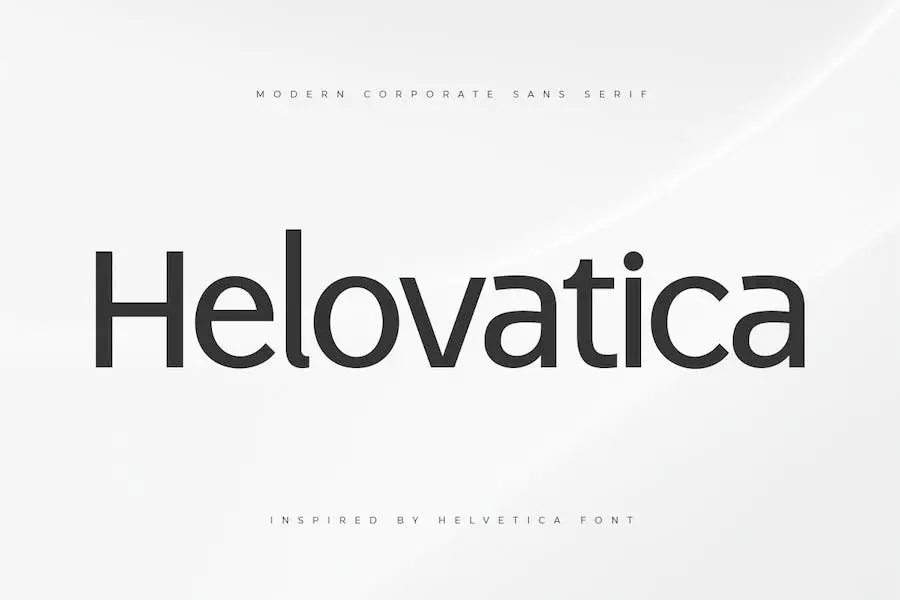
Helovatica este un font remarcabil corporativ sans serif, care emană o senzație modernă, elegantă și unică. Este alegerea perfectă pentru orice designer grafic care dorește să-și îmbunătățească proiectele cu o notă de clasă.
Acest font este conceput special pentru proiecte de design de logo, făcându-l ideal pentru crearea de logo-uri uimitoare care necesită o notă modernă.
Dar nu se oprește aici – Helovatica este suficient de versatil pentru a fi utilizat într-o gamă largă de aplicații, inclusiv branding, machete de reviste, grafică pentru rețelele sociale și multe altele.
Cu aspectul său elegant și rafinat, acest font va ridica cu siguranță designul oricărui proiect care are nevoie de o atmosferă modernă și sofisticată.
Ronald
Ronald este un nou font condensat sans serif conceput special pentru titluri, titluri și nevoi de tipografie. Este alegerea perfectă pentru a adăuga stilul tău personal și pentru a îmbunătăți aspectul general al proiectelor tale de design.
Acest font este special creat pentru a oferi o senzație unică și modernă titlurilor dvs., permițându-vă să vă prezentați ideile principale într-un mod atrăgător din punct de vedere vizual.
Cu Ronald, puteți crea cu ușurință modele atrăgătoare și profesionale care vă vor captiva publicul. Indiferent dacă lucrați la un site web, un logo sau orice alt proiect de design, acest font vă va ajuta să aveți un impact puternic și memorabil.
Natura condensată a lui Ronald îl face ideal pentru a încadra mai mult text în spații limitate, fără a compromite lizibilitatea sau estetica.
Liniile sale curate și marginile ascuțite îi conferă un aspect elegant și contemporan, făcându-l o alegere excelentă pentru branding corporativ, reclame sau orice design care necesită o notă îndrăzneață și profesională.
Garnitură
Gasket, un nou font Sans Serif, a fost creat special pentru proiecte de afaceri și corporative. Cu versiuni suplimentare de contur și cursive, adaugă o notă unică design-urilor tale. Stilul său curat și modern îl face perfect pentru propuneri și pentru a vă prezenta ideile principale într-un mod remarcabil.
Garnitura este concepută pentru a ridica atractivitatea vizuală a proiectului și pentru a oferi o notă profesională. Indiferent dacă lucrați la o prezentare de afaceri, la o marcă corporativă sau la o propunere, acest font vă acoperă.
Liniile sale îndrăznețe și curate îl fac ușor de citit, în timp ce versiunile suplimentare cu contur și italic vă oferă versatilitate și opțiuni pentru a vă juca.
Acest font este ideal pentru a vă transmite propunerea de valoare și pentru a face o impresie puternică. Senzația de curatare a garniturii va îmbunătăți estetica generală a proiectelor dvs. și vă va ajuta să vă evidențiați față de concurență.
Designul său modern și elegant emană profesionalism și încredere, făcându-l o alegere excelentă pentru orice cadru corporativ.
Corporația Dingbat
Corporate Dingbat este un font versatil și ușor de utilizat, care este perfect pentru designerii grafici care doresc să îmbunătățească designul proiectelor lor.
Cu colecția sa de 62 de simboluri, acest font simplu Doodle Doodle corporativ este potrivit pentru o gamă largă de aplicații, cum ar fi logo-uri, ornamente și multe altele.
Fontul adaugă o notă de profesionalism oricărui design, oferindu-i un aspect lustruit și sofisticat. Liniile sale curate și stilul minimalist îl fac ușor de încorporat în diverse proiecte, asigurând un aspect coeziv și profesional.
Indiferent dacă lucrați la un proiect de branding corporativ, creați un logo pentru un client sau doriți să sporiți interesul vizual al unui design, Corporate Dingbat oferă o gamă largă de simboluri din care să alegeți.
Versatilitatea sa permite posibilități creative nesfârșite, permițând designerilor să adauge elemente și note unice lucrării lor.
Proiectat ținând cont de nevoile designerilor grafici, acest font este ușor de utilizat și de navigat. Interfața sa ușor de utilizat asigură o experiență perfectă
Atac
Attack este un font Corporate Logo Sans Serif, elegant și modern, care va ridica designul oricărui proiect. Stilul său minimalist și iconic îl face alegerea perfectă pentru proiecte de branding, design de logo și design de poster.
Cu formele sale unice și ligaturile ușor de combinat, puteți crea variații nesfârșite pentru a se potrivi viziunii tale creative în doar câteva secunde.
Acest font nu este doar plăcut din punct de vedere estetic, dar oferă și un nivel ridicat de lizibilitate. Indiferent dacă proiectați postări pe rețelele sociale, reclame, ambalaje de produse sau etichete, Attack se va asigura că mesajul dvs. este clar și ușor de înțeles.
Este, de asemenea, o alegere excelentă pentru filigrane de fotografie, invitații și articole de papetărie, adăugând o notă de sofisticare proiectelor dvs.
Versatilitatea lui Attack îl face un atu valoros pentru designerii grafici. Liniile sale curate și prezența îndrăzneață îl fac potrivit pentru o gamă largă de aplicații.
Fie că țintiți la un aspect profesional și șlefuit sau la o senzație mai contemporană și mai modernă, acest font vă acoperă.
Paniscobe
Paniscobe este un font corporativ îndrăzneț care emană un sentiment de profesionalism și încredere. Aspectul său gros captează atenția și lasă o impresie de durată asupra oricărui proiect pentru care este folosit.
Fie că proiectați un logo elegant al companiei sau creați materiale de marketing atrăgătoare, Paniscobe este fontul pentru a vă ridica designul la următorul nivel.
Cu liniile sale curate și prezența puternică, Paniscobe se asigură că mesajul tău este transmis cu voce tare și clar. Contururile sale groase fac fiecare personaj să iasă în evidență, permițând o lizibilitate ușoară chiar și de la distanță.
Fie că este pe un site web, pe un afiș sau pe o carte de vizită, Paniscobe se asigură că textul tău nu va trece neobservat.
Acest font corporativ este perfect pentru a transmite un sentiment de putere și fiabilitate. Este ideal pentru industrii precum finanțele, tehnologia și consultanța, în care încrederea și credibilitatea sunt primordiale.
FT Getcode Pro
FT Getcode Pro este o familie modernă de fonturi slab serif care poate îmbunătăți foarte mult designul companiei sau proiectelor corporative.
Cu natura sa versatilă, acest font poate fi aplicat unei game largi de idei creative, făcându-le cu adevărat remarcate. Încorporarea FT Getcode Pro în design-ul dvs. le va oferi un aspect profesional și șlefuit, ridicându-vă brandingul și atrăgând atenția.
Fie că este vorba de logo-uri, anteturi de site-uri web sau materiale de marketing, acest font cu siguranță va avea un impact de durată. Extindeți-vă posibilitățile creative cu FT Getcode Pro și vedeți diferența pe care o poate face pentru fonturile dvs. de afaceri.
Krick Display
Krick Display este o nouă generație de caractere concepute special pentru a îmbunătăți atractivitatea mărcii dvs. Cu patru greutăți din care să alegeți, acest tip de caractere nu lasă neatins niciun detaliu. De la proiecte corporative la logo-uri, titluri și reclame digitale, Krick este suficient de versatil pentru a gestiona totul.
Indiferent dacă creați materiale de branding, titluri, postere sau ecrane de afișare, acest font vă acoperă. Designul său meticulos asigură că fiecare element se aliniază perfect, făcând din Krick alegerea supremă pentru designerii care doresc să facă o impresie de durată.
Gamarasa
Gamarasa este un font de afișare îndrăzneț și în stil robotic, care este perfect pentru a adăuga o notă unică proiectelor dvs. de design. Indiferent dacă aveți nevoie de un font pentru logo-ul dvs., titluri sau orice efort creativ, Gamarasa vă acoperă.
Cu designul său elegant și modern, acest font este potrivit pentru diverse aplicații, cum ar fi identitatea corporativă, identitatea mărcii, postere, muzică, filme, tipuri de jocuri, reviste, cărți, benzi desenate, desene animate, YouTube, Instagram, site-uri web și multe altele.
Una dintre caracteristicile remarcabile ale Gamarasa este aspectul său îndrăzneț și atrăgător. Liniile curate și formele geometrice puternice conferă acestui font o atmosferă robotizată și futuristă, făcându-l o alegere perfectă pentru proiectele care necesită un aspect modern și emotionant.
Va atrage instantaneu atenția spectatorilor și va face designul dvs. să iasă în evidență din mulțime.
În plus, Gamarasa este incredibil de versatil și poate fi ușor încorporat în diverse teme și stiluri de design.
Indiferent dacă lucrați la un proiect corporativ elegant și minimalist sau la un design de poster distractiv și vibrant, acest font se poate adapta nevoilor dvs. și poate îmbunătăți impactul vizual general al lucrării dvs.
prox
Prox este un font corporativ inovator care aduce un avantaj contemporan proiectelor dumneavoastră de design. Acest tip de caractere sans serif cu lățime îngustă este perfect pentru setarea textului atât în dimensiuni mari, cât și în dimensiuni mici.
Proporția sa ușor pătrată îi conferă un aspect unic și original, în timp ce formele obișnuite ale literelor oferă un sentiment de familiaritate. Indiferent dacă lucrați la o broșură, logo sau site web, Prox va adăuga o notă de sofisticare și profesionalism design-urilor dvs.
Una dintre caracteristicile remarcabile ale Prox este versatilitatea sa. Este potrivit pentru o varietate de aplicații de design, de la imprimare la digital.
Lățimea sa îngustă permite o lizibilitate ușoară, chiar și în spații înguste. Indiferent dacă creați o carte de vizită sau un antet de site, Prox se va asigura că textul dvs. iese în evidență și atrage atenția.
Un alt mare atribut al lui Prox este designul său modern și elegant. Formele de litere sans serif îi conferă un aspect curat și minimalist, făcându-l alegerea ideală pentru proiecte corporative și profesionale.
Aspectul său contemporan adaugă o notă de rafinament și eleganță oricărui design, păstrând în același timp un sentiment de familiaritate care îl face ușor de citit.
Breymont
Fontul Breymont este un caracter minimalist, elegant și rafinat, cu majuscule. Are o senzație modernă și contemporană, păstrând totuși o notă rafinată și funcțională.
Acest font unic și neortodox este perfect pentru o gamă largă de aplicații de design grafic, inclusiv design editorial și corporativ, precum și design web și interacțiune.
Indiferent dacă aveți nevoie să creați un logo elegant, să proiectați un site web uimitor sau să vă îmbunătățiți brandingul corporativ, Breymont se va simți întotdeauna bine și va adăuga o notă de sofisticare proiectelor dumneavoastră. Dimensiunile și sensul general îl fac o alegere versatilă, care vă va ridica cu siguranță design-urile.
Meridiana Pro
Meridiana Pro este un font cu aspect corporativ, care oferă o gamă largă de versatilitate și utilizare. Are două axe, greutate și cursiv și poate fi folosit ca font variabil sau ca familie OpenType separată.
Cu greutăți variind de la Subțire la Greu și oblicurile acestora, permite o gamă largă de posibilități de proiectare.
Unul dintre conceptele cheie din spatele Meridiana Pro a fost acela de a combina caracteristicile unui font rotunjit sans cu cele ale unui font monospațial. Acest amestec unic are ca rezultat un sistem de tip extins și utilizabil, care poate fi adaptat la diferite proiecte de design.
Pe lângă versatilitatea sa, acest font oferă și o gamă largă de alternative, ligaturi și simboluri. Are suport lingvistic extins pentru majoritatea limbilor europene, ceea ce îl face potrivit pentru proiecte internaționale.
Designul Meridiana Pro se caracterizează prin ritmul său simetric și echilibrat. Proporțiile au fost ajustate cu precizie, iar contururile sunt netede, cu contraste subtile.
Acest lucru conferă fontului un aspect atrăgător, fără a sacrifica eleganța și minimalismul. Fiecare glifă a fost realizată cu atenție pentru a se asigura că funcționează bine în orice scop de design grafic.
Scena Grotesk
Stage Grotesk este un font clasic sans-serif care prioritizează perfecțiunea și lizibilitatea. Cu accent pe minimalism și simplitate, acest tip de caractere ridică proiectele dvs. de design la noi niveluri de atractivitate vizuală.
Ideal pentru design grafic, design web, imprimare și utilizare afișării, Stage Grotesk este o opțiune versatilă. Face minuni pentru branding, design de logo, grafică de marketing, bannere, postere, semnalizare, identități corporative și design editorial. Stilul curat și elegant al fontului este perfect pentru titluri și logotipuri minime, așa cum se arată în imaginile promoționale.
Pachetul include diverse formate de fișiere, cum ar fi OTF, TTF și fonturi web (inclusiv EOT, SVG, WOFF). În plus, setările și demonstrațiile HTML și CSS WebFont sunt incluse în pachetul de descărcare.
Stage Grotesk oferă un total de 14 fonturi, cu 7 greutăți variind de la Thin la Black. Fiecare greutate este disponibilă atât în versiune verticală, cât și în versiuni italice, oferind flexibilitate pentru nevoile dvs. de proiectare.
Această familie de fonturi este realizată manual și proiectată cu funcții OpenType puternice, asigurând suport extins pentru limbi pentru seturile din Europa de Vest și Europa Centrală.
RNS Miles
RNS Miles este o familie de fonturi cursive corporative care combină forme geometrice, forme deschise și o stare de spirit Grotesk pentru a crea un design armonios și neutru.
Inspirat de modernism, este conceput special pentru titluri, titluri și subtitrări. Cu 7 greutăți, de la subțire la negru, fiecare greutate vine cu un stil italic potrivit.
Ceea ce diferențiază RNS Miles sunt caracteristicile sale extinse OpenType, inclusiv glife alternative, fracții, săgeți, cifre vechi, numărători, numitori și o gamă largă de simboluri și suport pentru limbaj.
Acest lucru le permite designerilor grafici să adauge proiecte unice și personalizate.
Cu formele sale cu contrast redus și estetica modernă, RNS Miles este un font versatil care adaugă un aspect elegant și profesional oricărui design. Indiferent dacă lucrați la un logo, un site web sau un material de tipărit, această familie de fonturi oferă o tipografie curată și atrăgătoare.
Mugio
Vă prezentăm Mugio, un font corporativ îndrăzneț care este cu adevărat unic. Acest font versatil este perfect pentru orice proiect pe care îl aveți în minte. Cu literele sale înclinate și curbele elegante, Mugio este ideal pentru postere, logo-uri, fluturași și multe altele.
Indiferent dacă proiectați o prezentare profesională sau creați reclame atrăgătoare, acest font vă acoperă.
Una dintre calitățile remarcabile ale Mugio este familia sa de fonturi, care include opțiuni pentru titluri, subtitrări și text de propoziție. Acest lucru vă permite să mențineți un aspect și o senzație consistentă pe parcursul întregului proiect.
Luați rămas bun de la necazul căutării diferitelor fonturi care se completează reciproc – Mugio are tot ce aveți nevoie într-un singur pachet.
Utilizarea Mugio pentru proiectele dumneavoastră de design vă garantează că acestea vor fi cu adevărat extraordinare. Îndrăzneala și sofisticarea acestui font adaugă o notă de profesionalism și eleganță lucrării tale. Atrage atenția fără efort și face o impresie de durată asupra publicului tău.
Deci, de ce să așteptați? Începeți să utilizați Mugio astăzi și duceți-vă design-urile la nivelul următor. Proiectele tale vor ieși în evidență din mulțime și vor lăsa o impresie de durată asupra oricui le vede. Îmbrățișați puterea și versatilitatea Mugio și urmăriți-vă desenele prind viață.
Biomorf
Vă prezentăm Biomorph, o nouă familie de fonturi condensate sans. Acest font este perfect pentru proiectele dvs., fie că proiectați materiale de branding, publicați conținut, creați titluri sau lucrați la un site web.
Cu versiunile sale subțiri, foarte ușoare, obișnuite, medii, semiîndrăznețe și îndrăznețe, Biomorph vă oferă libertatea de a proiecta după cum doriți. Spune adio limitărilor și salută posibilitățile nesfârșite cu această familie de fonturi versatilă”.
„Fonturile corporative pentru Figma nu au fost niciodată mai interesante cu lansarea Biomorph. Această familie de fonturi este o schimbare de joc pentru designerii grafici care doresc să-și ridice proiectele.
Indiferent dacă lucrați la o carte, un aspect al unei reviste sau un design de site web, Biomorph vă acoperă. Stilul său sans condensat aduce o notă modernă și sofisticată lucrării tale, sporind instantaneu atractivitatea sa vizuală”.
„Conceput cu versatilitatea în minte, Biomorph oferă o gamă de greutăți, de la subțire la îndrăzneț. Acest lucru înseamnă că puteți experimenta diferite stiluri și puteți crea un aspect coeziv în întregul design.
Vectro
Vectro este un font sans condensat obișnuit și curat, care este perfect pentru a crea branding corporativ puternic, reclame de copiere, logotipuri și multe altele. Oferă un aspect profesional și elegant oricărui proiect de design.
Liniile sale curate și estetica modernă îl fac favorit printre designerii grafici care doresc să-și ridice munca la următorul nivel.
Acest font sans serif este conceput special pentru a îmbunătăți proiectele corporative și pentru a oferi un aspect curat și sofisticat. Cu stilul său condensat, Vectro este capabil să încadreze mai multe caractere pe o linie, permițând afișarea mai multor text într-un spațiu limitat.
Este ideal pentru titluri, titluri și chiar textul corpului atunci când se dorește un aspect elegant și profesional.
Una dintre caracteristicile remarcabile ale Vectro este versatilitatea sa. Poate fi folosit pentru o gamă largă de proiecte, de la rapoarte și prezentări corporative până la materiale publicitare și design web. Stilul său curat și casual îl face potrivit atât pentru aplicații formale, cât și pentru cele informale.
Osande TXT
Osande TXT este o familie de fonturi versatilă care oferă caractere îmbunătățite și suport lingvistic cuprinzător, făcându-l o alegere ideală pentru o gamă largă de proiecte de design. Indiferent dacă lucrați la corpul textului sau la elemente de afișare, această familie de fonturi vă oferă flexibilitatea de care aveți nevoie.
Inspirat de stilul modern sans al lui „Osande Pro”, Osande TXT încorporează elemente de fonturi neo-grotescuri și neo-gotice.
Cu înălțimea sa mare x, formele simplificate și designul static, cu contrast scăzut, această familie de fonturi emană o atmosferă contemporană. În plus, lățimea condensată adaugă o notă de eleganță.
Una dintre caracteristicile remarcabile ale Osande TXT este suportul lingvistic îmbunătățit. Indiferent de limbă, această familie de fonturi vă oferă acoperire, asigurând o integrare perfectă în design-urile dvs.
Din engleză în alte limbi, veți găsi personajele de care aveți nevoie pentru a comunica eficient.
Popstick
Popstick este un font grozav în stil pop art, care vă va duce designul la nivelul următor. Cu aspectul său modern, curat și proaspăt, este perfect pentru a adăuga o notă de sofisticare oricărui proiect.
Forma rotunjită a literelor îi conferă un finisaj frumos, lustruit, care cu siguranță va impresiona. Indiferent dacă lucrați la publicitate, ambalaj, un logo sau identitate corporativă, Popstick este alegerea ideală. Versatilitatea sa îl face potrivit pentru o gamă largă de utilizări comerciale și editoriale.
Deci, de ce să vă mulțumiți cu fonturi obișnuite când puteți adăuga un unic și ochi-ca
Cele mai bune fonturi corporative gratuite
Bine ați venit în lumea fonturilor, unde cel potrivit poate face toată diferența în proiectele dvs. de design. În această secțiune, vom explora unele dintre cele mai bune fonturi corporative gratuite disponibile, perfecte pentru a adăuga un plus de profesionalism și eleganță muncii dvs.
Deci, de ce să nu aruncați o privire la aceste alegeri de top și să descoperiți fontul perfect pentru a vă îmbunătăți jocul de design?
Sediul central al companiei
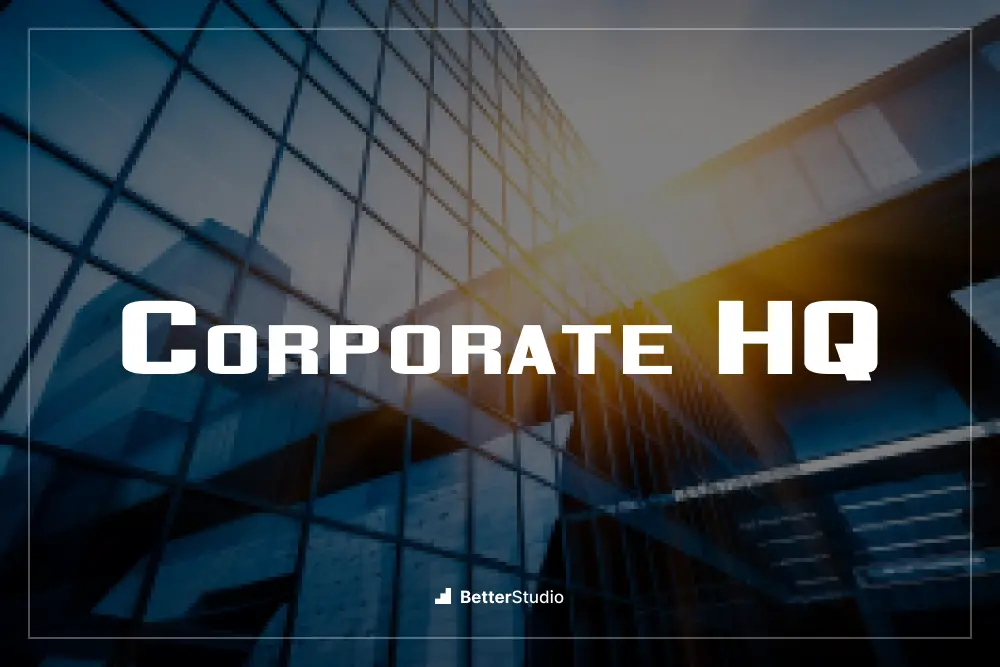
Corporate HQ by Vic Fieger este un font obligatoriu pentru designerii grafici care doresc să îmbunătățească designul proiectelor lor. Acest font îndrăzneț și profesional emană un sentiment de sofisticare și eleganță care este perfect pentru branding corporativ și comunicare vizuală.
Cu liniile sale curate și prezența puternică, Corporate HQ adaugă o notă de profesionalism oricărui design. Indiferent dacă lucrați la un logo, la un site web sau la materiale tipărite, acest font vă va ridica proiectul la nivelul următor.
Unul dintre atributele remarcabile ale sediului corporativ este versatilitatea sa. Este foarte lizibil și funcționează bine atât la dimensiuni mari, cât și la dimensiuni mici. Aceasta înseamnă că îl puteți folosi pentru titluri, textul corpului sau chiar ca element decorativ în desenele dvs.
Îndrăzneala fontului asigură că captează atenția, păstrând în același timp un aspect elegant și modern.
O altă caracteristică grozavă a sediului corporativ este setul extins de caractere. Include o gamă largă de caractere speciale, simboluri și semne diacritice, făcându-l potrivit pentru proiecte multilingve. Acest font are cu adevărat tot ce aveți nevoie pentru a răspunde cerințelor diverse de design.
Fără zgură
Slagless de la Almarkhatype este un font de top care este perfect pentru designerii grafici care doresc să-și îmbunătățească proiectele cu o notă îndrăzneață și corporativă. Cu estetica sa elegantă și modernă, acest font este garantat să facă o declarație și să ridice orice design.
Unul dintre atributele remarcabile ale Slagless este versatilitatea sa. Indiferent dacă lucrați la un logo, un ambalaj sau un site web, acest font se va adapta perfect oricărui proiect, adăugând un aspect profesional și șlefuit.
Liniile sale îndrăznețe și curate îi conferă o senzație contemporană, păstrând în același timp un aspect corporativ.
O altă caracteristică excelentă a Slagless este lizibilitatea sa. Cu o combinație echilibrată de linii groase și subțiri, acest font este ușor pentru ochi, asigurând că mesajul dvs. este transmis fără efort spectatorilor.
Indiferent dacă este pe un material tipărit sau pe o platformă digitală, Slagless se va asigura că textul tău rămâne clar și lizibil.
Qiunels
Qiunels de la Almarkhatype este un font cursiv corporativ fantastic care vă va ridica proiectele de design la următorul nivel. Cu curbele elegante și elegante, Qiunels adaugă o notă de rafinament și profesionalism oricărui design.
Acest font este perfect pentru designerii grafici care doresc să creeze logo-uri atrăgătoare, cărți de vizită elegante, prezentări impresionante și multe altele.
Qiunels oferă o gamă largă de greutăți și stiluri, permițându-vă să găsiți potrivirea perfectă pentru proiectul dvs. Fie că sunteți în căutarea unui font îndrăzneț și de impact sau a unei opțiuni mai subestimate și rafinate, Qiunels vă acoperă.
Versatilitatea sa asigură că poate fi folosit într-o varietate de contexte și va face întotdeauna o impresie puternică.
Una dintre caracteristicile remarcabile ale Qiunels este lizibilitatea sa. Chiar și cu stilul său cursiv, fontul rămâne foarte lizibil, ceea ce îl face o alegere excelentă atât pentru proiectele tipărite, cât și pentru cele digitale. Captează fără efort atenția fără a sacrifica claritatea, asigurându-se că mesajul tău este transmis în mod eficient.
Walterosse
Walterosse este un font cursiv corporativ fantastic creat de Almarkhatype. Cu designul său elegant și profesional, acest font este perfect pentru designerii grafici care doresc să îmbunătățească aspectul proiectelor lor.
Curbele sale elegante și literele bine definite adaugă o notă de sofisticare oricărui design.
Unul dintre atributele remarcabile ale lui Walterosse este versatilitatea sa. Indiferent dacă lucrați la un logo, un site web sau materiale de marketing, acest font vă poate ridica designul la următorul nivel.
Aspectul său curat și lizibil îl face ușor de citit, chiar și la dimensiuni mai mici, asigurând că mesajul dvs. este transmis în mod eficient.
O altă caracteristică impresionantă a lui Walterosse este atenția la detalii. Fiecare literă a fost elaborată meticulos pentru a menține un sentiment de echilibru și armonie.
Acest font emană profesionalism și rafinament, făcându-l o alegere excelentă pentru branding corporativ sau orice proiect care necesită o notă de sofisticare.
Alice Yotsuba Inc.
Alice Yotsuba Inc. este un font foarte recomandat pentru designerii grafici care doresc să-și îmbunătățească designul proiectelor. Acest font Corporate Sans Serif, creat de Unicoder2020, oferă o gamă de atribute care îl fac o alegere ideală pentru modelele profesionale.
Cu aspectul său elegant și modern, Alice Yotsuba Inc. aduce o notă sofisticată oricărui proiect de design grafic. Liniile sale curate și proporțiile echilibrate creează un sentiment de profesionalism și eleganță, făcându-l perfect pentru materiale de branding corporative, prezentări și site-uri web.
Una dintre caracteristicile remarcabile ale Alice Yotsuba Inc. este versatilitatea sa. Indiferent dacă lucrați la un design de logo, un proiect de tipografie sau orice alt element vizual, acest font se poate adapta fără probleme la diferite stiluri și scopuri de design.
Atractia sa atemporală asigură faptul că rămâne relevantă și de impact pentru anii următori.
De mai sus
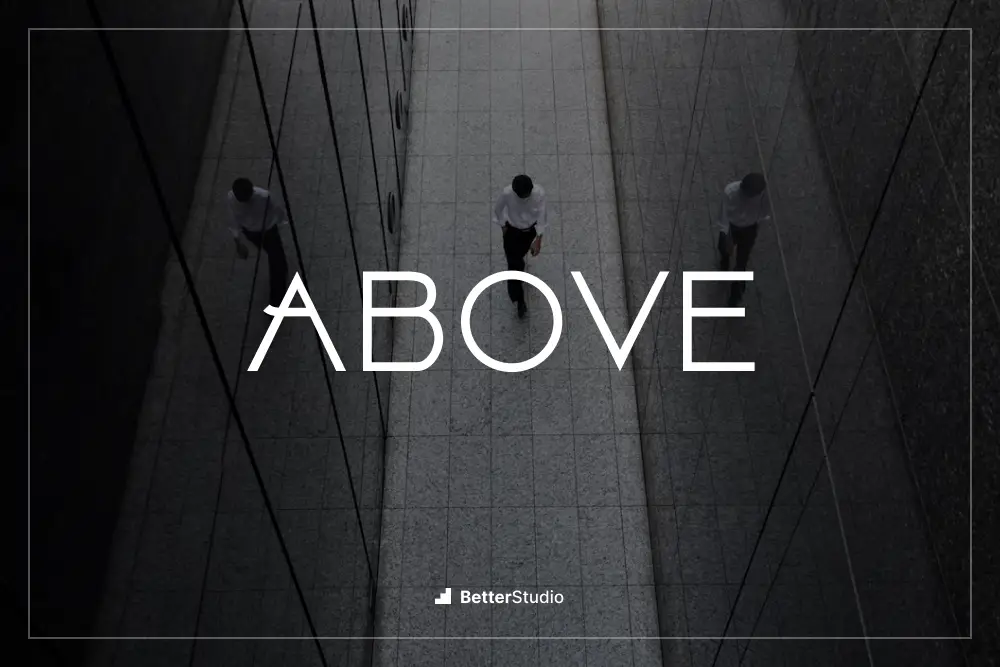
Above by Herofonts este un font corporativ sans serif care este perfect pentru designerii grafici care doresc să îmbunătățească designul proiectelor lor. Acest font emană profesionalism și sofisticare, făcându-l ideal pentru orice nevoi de design corporative sau legate de afaceri.
Deasupra are un aspect curat și elegant, cu linii ascuțite și proporții echilibrate. Designul său simplu, dar elegant, permite o lizibilitate ușoară, făcându-l o alegere versatilă pentru diverse aplicații de design.
Indiferent dacă lucrați la un logo, la un site web sau la materiale de imprimare, Above vă va ridica designul și îi va oferi un aspect șlefuit și profesional.
Una dintre caracteristicile remarcabile ale Above este gama sa extinsă de greutăți și stiluri. Oferă o varietate de opțiuni, de la ușoare la îndrăznețe, permițându-vă să personalizați grosimea fontului pentru a se potrivi cerințelor dvs. specifice de design.
Această versatilitate asigură că Above poate fi utilizat în diverse contexte fără a-i compromite impactul.
În plus, Above se mândrește cu un set cuprinzător de caractere care include litere mari și mici, numere, semne de punctuație și caractere speciale.
Această gamă largă de personaje vă asigură că aveți tot ce aveți nevoie pentru a crea design-uri izbitoare și captivante.
Şanţ
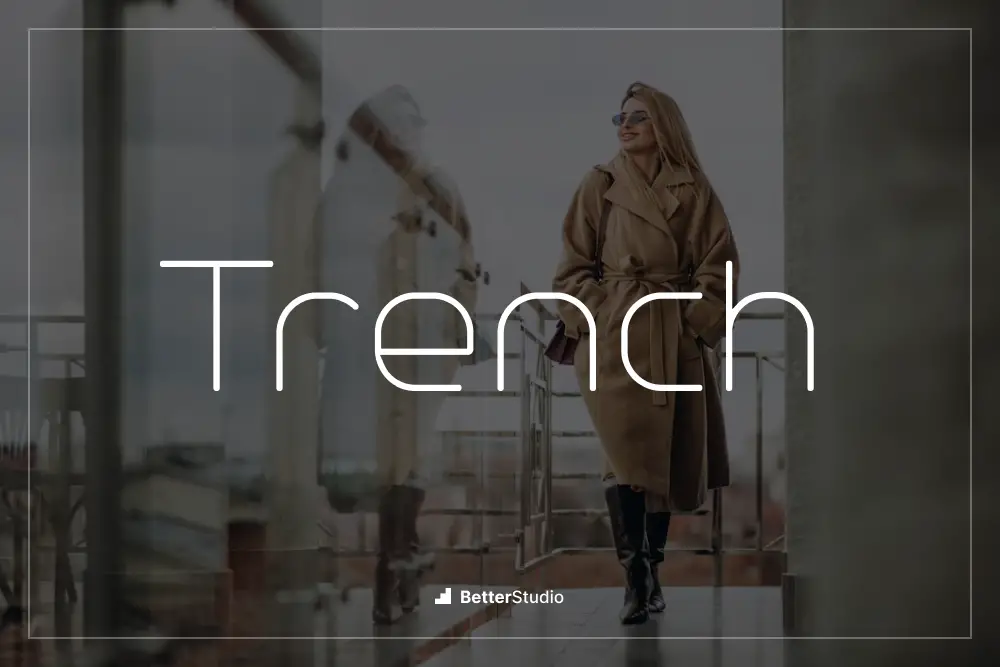
Trench by NimaType este un font corporativ sans serif versatil și elegant. Oferă o gamă largă de atribute care îl fac o alegere perfectă pentru designerii grafici care doresc să îmbunătățească designul proiectelor lor.
Cu designul său curat și modern, Trench adaugă o notă de profesionalism oricărui proiect corporativ. Estetica sa simplă, dar atemporală, îl face potrivit pentru diverse aplicații, de la logo-uri și branding până la materiale de marketing și design de site-uri web.
Una dintre caracteristicile remarcabile ale lui Trench este setul extins de glife. Include o gamă largă de personaje, inclusiv ligături și supleanți, permițând designerilor să creeze o tipografie unică și atractivă vizual.
Acest font oferă, de asemenea, mai multe greutăți, oferind utilizatorilor flexibilitatea de a alege stilul potrivit pentru nevoile lor specifice.
Paris Van Java
Paris Van Java este un font corporativ remarcabil sans serif creat de fikryalstudio. Acest font este perfect pentru designerii grafici care doresc să îmbunătățească designul proiectelor lor. Cu un aspect curat și profesional, Paris Van Java adaugă o notă de eleganță oricărui design.
Versatilitatea sa îi permite să fie utilizat în diverse aplicații, de la branding și ambalare până la designul site-urilor web și materialele de imprimare. Cu aspectul său elegant și modern, acest font va impresiona cu siguranță clienții și va ridica estetica generală a lucrării dvs.
Este timpul să vă duceți proiectele de design la următorul nivel cu Paris Van Java. Deci, de ce să așteptați? Încercați-l astăzi și aduceți un nou nivel de sofisticare design-urilor dvs.
NEOTERIC
NEOTERIC de Herofonts este un font corporativ sans serif versatil și modern, care vă va ridica proiectele de design grafic. Cu designul său curat și elegant, este alegerea perfectă pentru a crea un aspect profesional și lustruit.
Acest font are o serie de atribute atractive. Simplitatea sa permite o lizibilitate ușoară, făcându-l potrivit pentru o gamă largă de aplicații.
Liniile clare și rafinate ale NEOTERIC emană un sentiment de sofisticare și profesionalism, făcându-l o alegere ideală pentru branding corporativ, design de logo și materiale de marketing.
Formele de litere realizate cu atenție ale lui NEOTERIC asigură lizibilitatea chiar și la dimensiuni mai mici, păstrând în același timp impactul și atractivitatea vizuală. Acest font se potrivește bine cu alte elemente de design și poate fi încorporat cu ușurință în diferite stiluri de design, de la minimalist la îndrăzneț și atrăgător.
În plus, NEOTERIC oferă o gamă largă de greutăți, permițându-vă să experimentați și să găsiți echilibrul perfect pentru nevoile dvs. de design. Indiferent dacă doriți să transmiteți un sentiment de autoritate cu o greutate îndrăzneață sau să optați pentru o greutate mai ușoară pentru o atingere mai delicată, acest font vă acoperă.
Austragen
Austragen by Almarkhatype este o alegere fantastică de font pentru designerii grafici care doresc să îmbunătățească designul proiectelor lor. Cu stilul său cursiv elegant și sofisticat, acest font adaugă o notă de profesionalism și clasă oricărui design corporativ.
Unul dintre atributele remarcabile ale Austragen este versatilitatea sa. Indiferent dacă lucrați la o siglă, o carte de vizită sau un site web, acest font se adaptează perfect la diferite elemente de design, făcându-l o alegere ideală pentru toate nevoile dvs. de fonturi corporative.
O altă caracteristică excelentă a Austragen este lizibilitatea sa. Literele sunt proiectate meticulos pentru a asigura o lizibilitate clară și clară, chiar și la dimensiuni mai mici. Acest lucru îl face perfect pentru text, titluri sau orice alt text care trebuie să fie citit cu ușurință de către publicul dvs.
Atenția la detalii în Austragen este cu adevărat impresionantă. Fiecare literă este realizată cu precizie, rezultând un font care arată impecabil și profesional. Curbele minunate curgătoare și liniile elegante oferă proiectelor dumneavoastră un aspect rafinat și lustruit.
Pe lângă atractivitatea sa estetică, Austragen oferă și o gamă largă de alternative stilistice și ligaturi. Aceste personaje suplimentare vă permit să experimentați și să creați modele unice și atrăgătoare, care ies cu adevărat în evidență din mulțime.
Poarta lunii
Moonglade de Herofonts este un font fantastic Corporate Sans Serif pe care designerii grafici îl pot folosi pentru a-și îmbunătăți designul proiectelor. Acest font emană profesionalism și eleganță, făcându-l perfect pentru branding corporativ, logo-uri, broșuri și site-uri web.
Moonglade se mândrește cu un design curat și atemporal, cu formele sale îndrăznețe și elegante, care fac fiecare literă să iasă în evidență. Marginile ascuțite și spațierea bine echilibrată oferă un sentiment de sofisticare, menținând totuși lizibilitatea la orice dimensiune.
Cu Moonglade, desenele tale vor avea un aspect rafinat și lustruit. Versatilitatea fontului îi permite să fie asociat atât cu fonturi serif, cât și cu fonturi script, oferindu-vă opțiuni nesfârșite pentru combinații creative.
Indiferent dacă proiectați pentru un brand de modă de ultimă generație, un startup de tehnologie modernă sau o instituție financiară tradițională, Moonglade vă va ridica fără efort design-urile.
Folosind Moonglade în proiectele dvs., puteți obține o estetică consecventă și profesională în materialele dvs. de branding. Setul extins de caractere al fontului acceptă mai multe limbi, asigurând că mesajul dvs. va ajunge la un public global.
ALTERON
ALTERON de la Absonstype este o alegere fantastică pentru designerii grafici care doresc să-și ridice designul proiectelor cu un font cursiv corporativ. Acest font emană sofisticare și profesionalism, făcându-l perfect pentru design-uri legate de afaceri.
Unul dintre atributele remarcabile ale ALTERON este stilul său cursiv elegant și rafinat. Fiecare literă curge perfect în următoarea, creând un aspect vizual plăcut și coeziv. Acest font cursiv adaugă o notă de clasă oricărui design, fie că este vorba despre un logo, site web sau materiale de imprimare.
Pe lângă atractivitatea sa estetică, ALTERON oferă o lizibilitate excelentă. Formele de litere realizate cu grijă asigură că fiecare caracter este ușor de distins, chiar și la dimensiuni mici. Acest lucru îl face ideal pentru textul corpului din documente corporative sau prezentări.
Un alt avantaj al ALTERON este versatilitatea sa. Este compatibil atât cu mediile digitale, cât și cu mediile tipărite, permițând designerilor să-l încorporeze fără probleme în diverse proiecte.
Cu ALTERON, puteți crea branding coerent pe diferite platforme, întărind identitatea corporativă a clientului dvs.
întrebări frecvente
Fonturile corporative sunt fonturi specifice alese de companii pentru a-și reprezenta identitatea mărcii. Ele joacă un rol crucial în crearea unei imagini consistente și profesionale pentru o afacere.
A avea un font corporativ bine definit ajută la stabilirea recunoașterii mărcii, la construirea încrederii cu clienții și la transmiterea valorilor și personalității companiei.
Fontul corporativ potrivit poate îmbunătăți în mod semnificativ designul general al materialelor unei companii. Acesta adaugă atractivitate vizuală, transmite un sentiment de profesionalism și ajută la crearea unei identități de brand coezive pe diverse platforme.
Alegând un font care se aliniază cu valorile companiei și cu publicul țintă, companiile pot crea o experiență plăcută vizual și memorabilă pentru clienții lor.
Ar trebui luați în considerare mai mulți factori atunci când alegeți un font corporativ. În primul rând, ar trebui să se alinieze cu identitatea de marcă a companiei și să reflecte personalitatea acesteia. În al doilea rând, lizibilitatea este crucială, în special pe diferite medii și dimensiuni.
În plus, fontul ar trebui să fie suficient de versatil pentru a fi utilizat în diferite materiale de marketing. În cele din urmă, luarea în considerare a publicului țintă și a tendințelor din industrie poate ajuta la alegerea unui font care rezonează cu oamenii potriviți.
Concluzie
În concluzie, am explorat cele mai bune 36 de fonturi corporative care pot îmbunătăți designul proiectelor dumneavoastră. De la clasic și elegant la modern și elegant, aceste fonturi oferă o gamă largă de opțiuni pentru a se potrivi nevoilor dumneavoastră de design corporativ.
Nu uitați să experimentați și să găsiți fontul care se aliniază cel mai bine cu personalitatea și mesajul mărcii dvs.